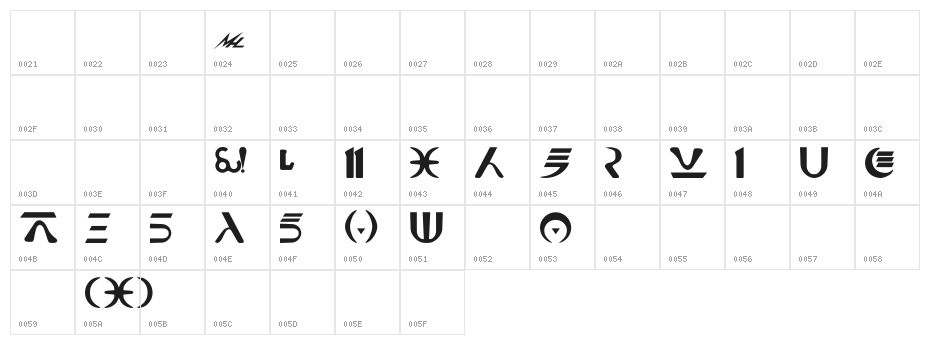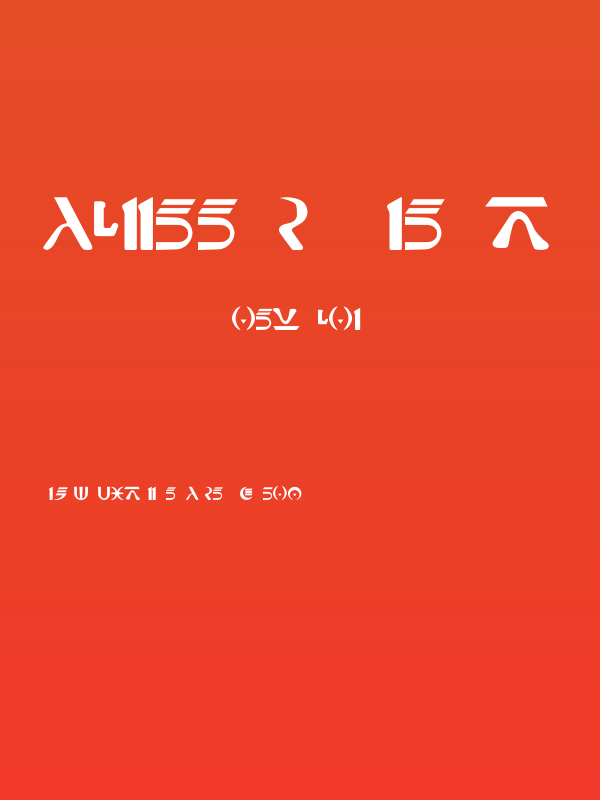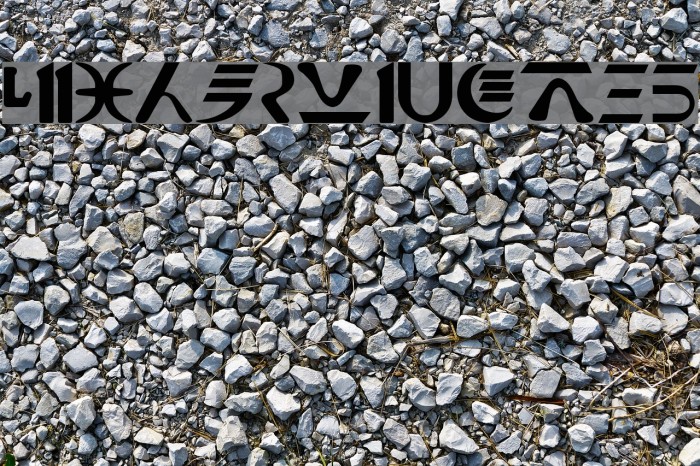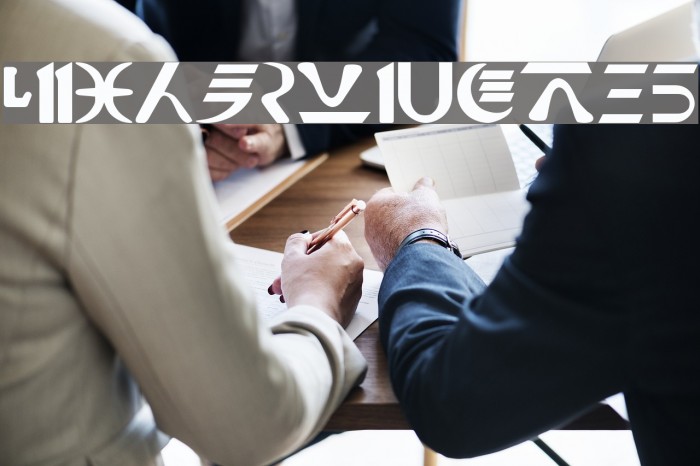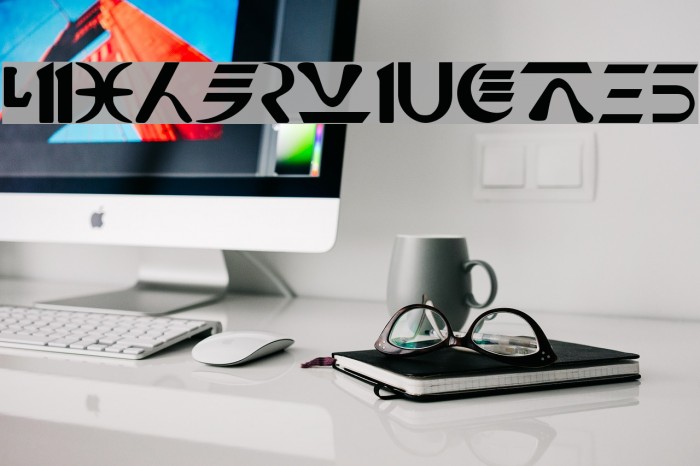
Naboo_Futhork Font
| Stil general | Futuristic |
| Proiecte propuse | Ideal for sci-fi themed projects, video game interfaces, movie posters, and branding for tech companies. |